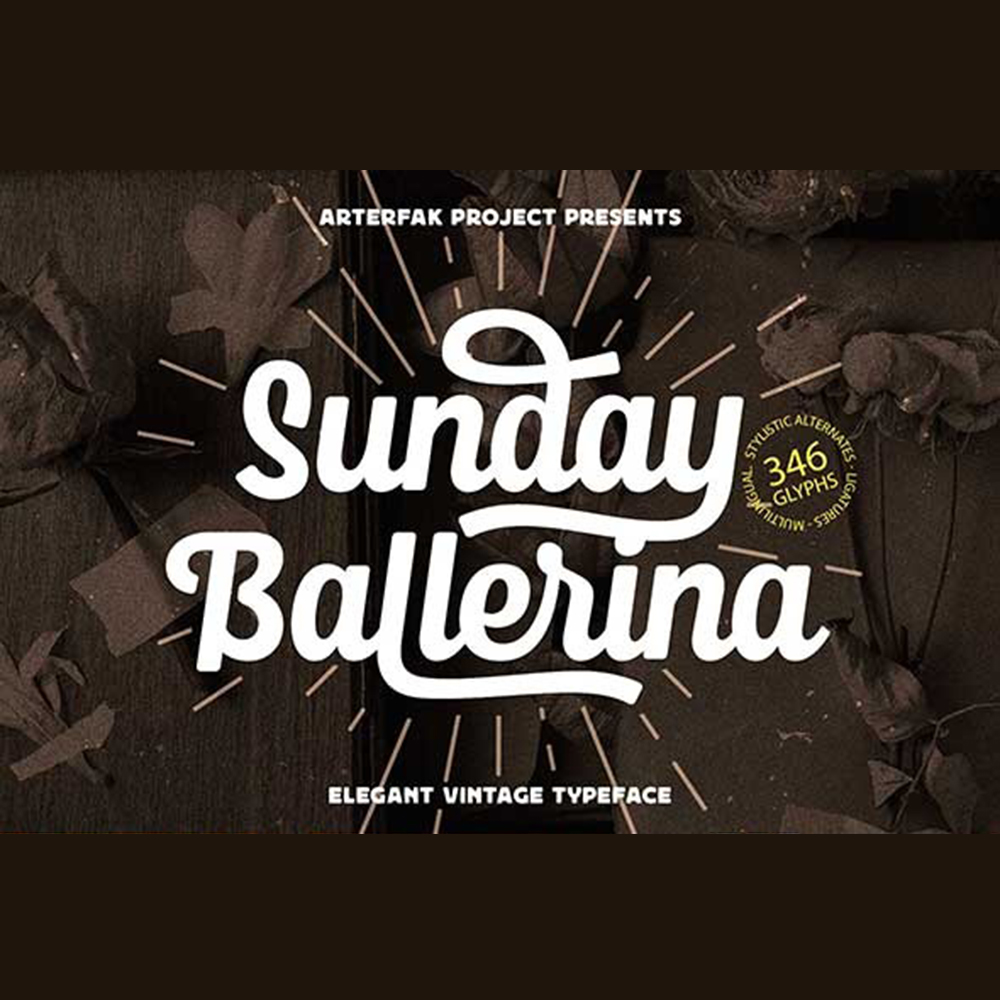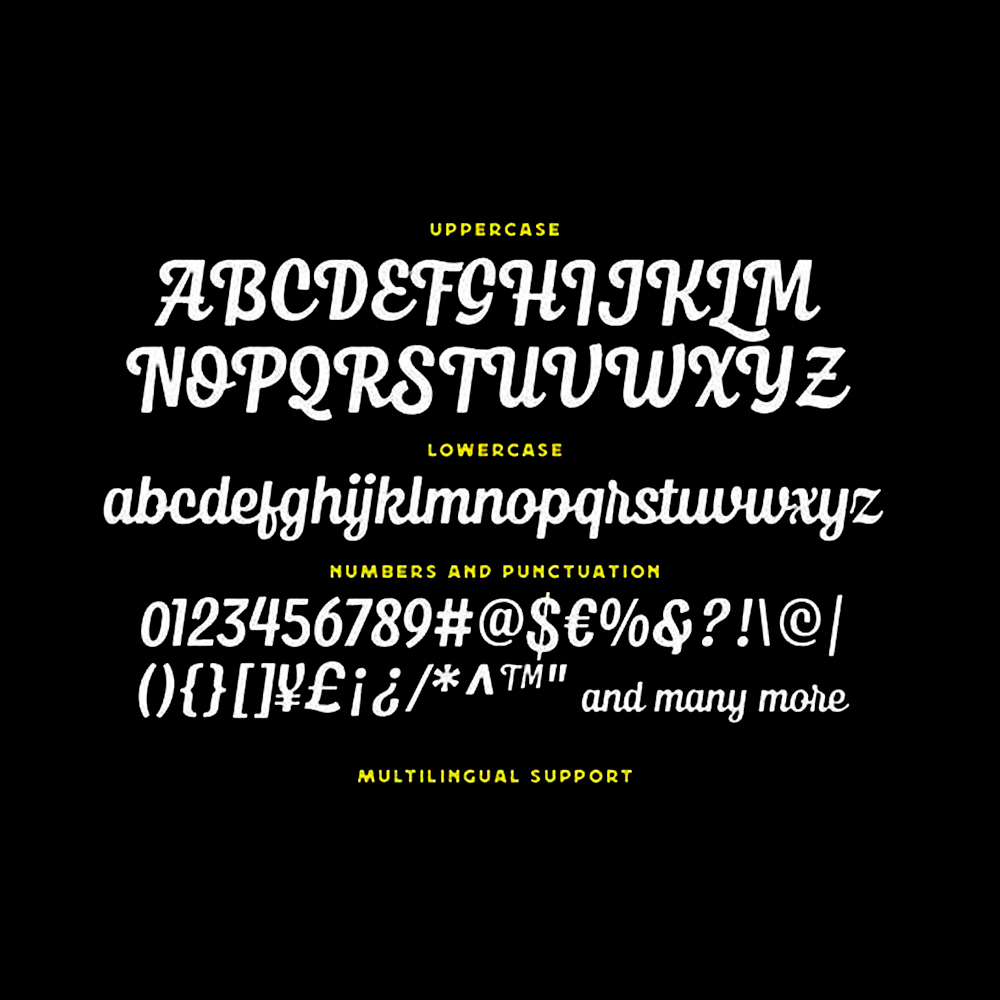
فونت پرمیوم و انگلیسی Sunday Ballerina Font، یک فونت تکخطی خیرهکننده قدیمی که به طور یکپارچه تایپوگرافی قدیمی را با لمس مدرن ترکیب میکند و ظرافت و پیچیدگی را به نمایش میگذارد. ایدهآل برای طیف گستردهای از کاربردها، از جمله لوگو، تابلو، کارت، برچسب، پوستر، موشن گرافیک، لوگوتایپ، برندسازی، پوشاک، کالا و موارد دیگر. این فونت همهکاره میتواند با تمهای مختلفی مانند قدیمی، ورزشی، رترو، ماجراجویی، مینیمالیستی، غذا و نوشیدنی، تعطیلات، شهری و بسیاری دیگر سازگار شود. Sunday Ballerina با جایگزینها و کاراکترهای swash متعدد ارائه میشود و به شما انعطافپذیری لازم برای ایجاد طرحهای تایپوگرافی منحصر به فرد و متنوع را میدهد.
مزایای استفاده از فونت لاتین Sunday Ballerina چیست؟